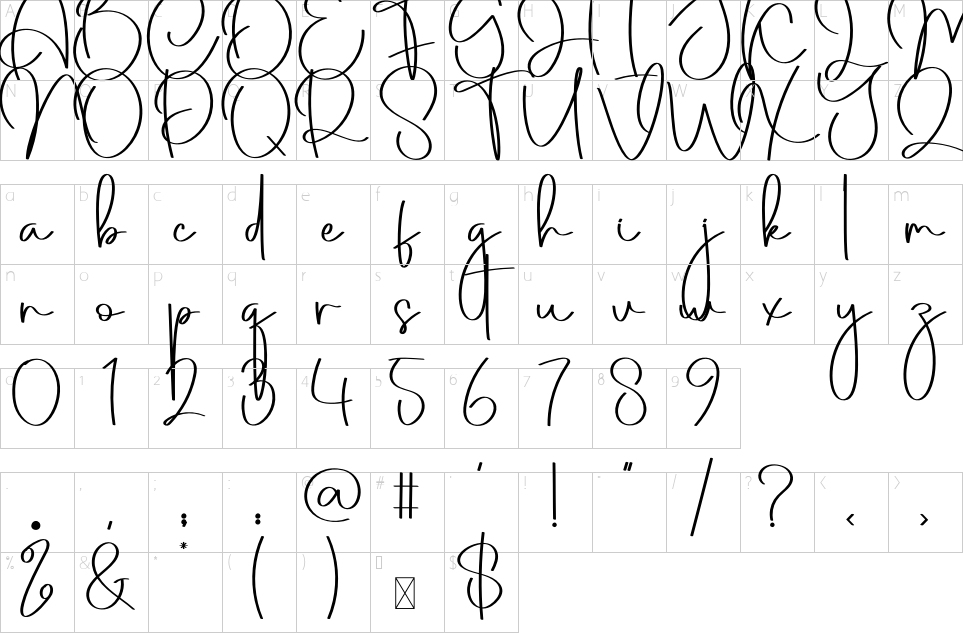
Aqui está uma descrição em português do Brasil, envolvente e natural, para uma página de download da fonte Alphabet: Acessível para usuários de Windows e Mac, a fonte Alphabet oferece um design limpo e fácil de ler. Desenvolvida pelo designer desconhecido, “scratchones”, a fonte Alphabet foi projetada com um equilíbrio perfeito entre simplicidade e estética. Seus caracteres são ideais para qualquer tipo de projeto, seja para criar títulos chamativos e profissionais ou textos mais discretos. Com um design minimalista e uma caligrafia agradável, a fonte Alphabet é perfeita para os criadores de conteúdo que buscam um estilo que se destaca, mas sem exageros. Com versões compatíveis com sistemas operacionais Windows e Mac, é fácil incorporar a Alphabet em projetos digitais, criando textos impecáveis em qualquer dispositivo. Compartilhe essa fonte com os seus projetos, é uma escolha inteligente para qualquer designer gráfico ou profissional de marketing digital em busca de uma fonte de alta qualidade para seus trabalhos.